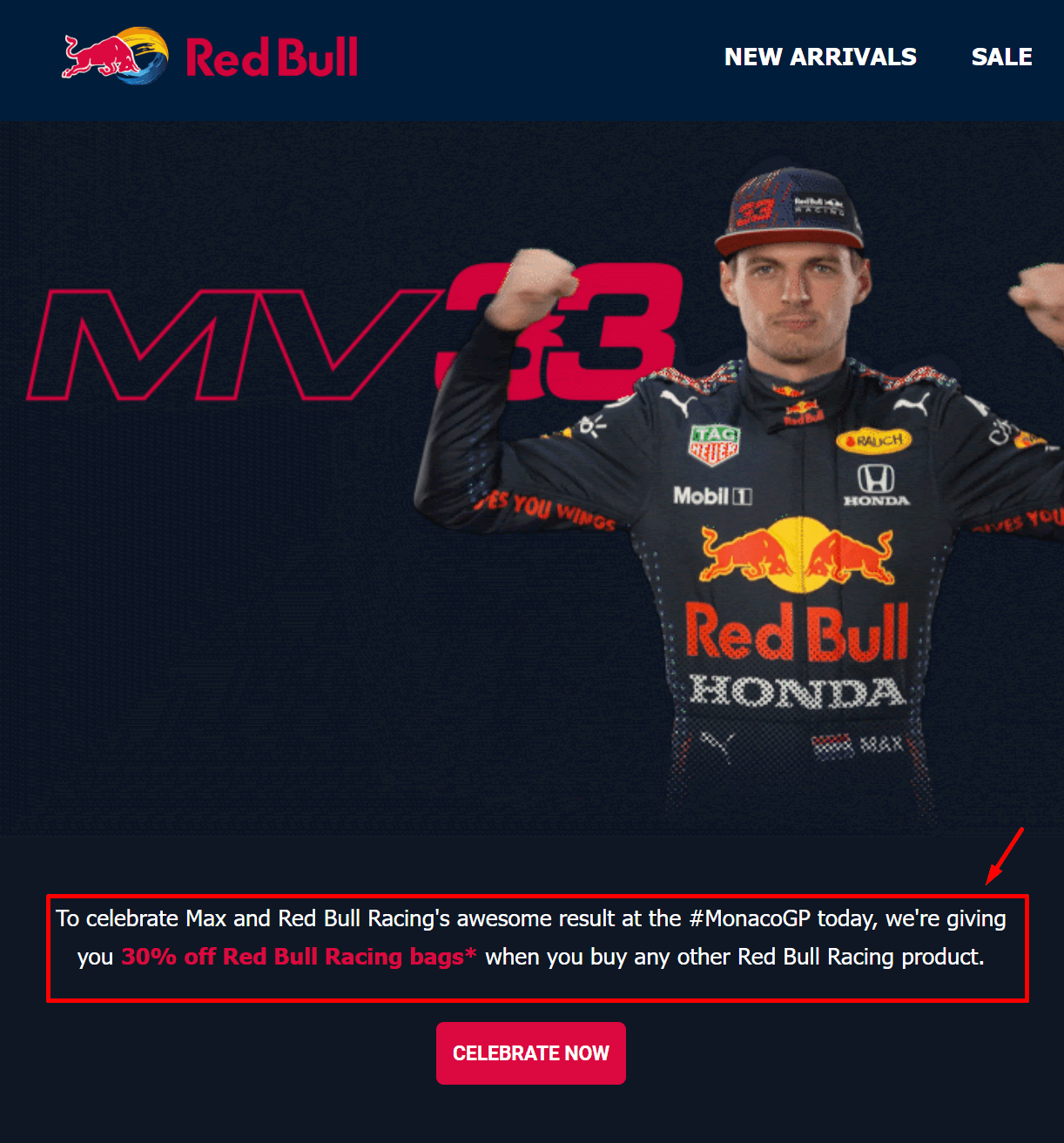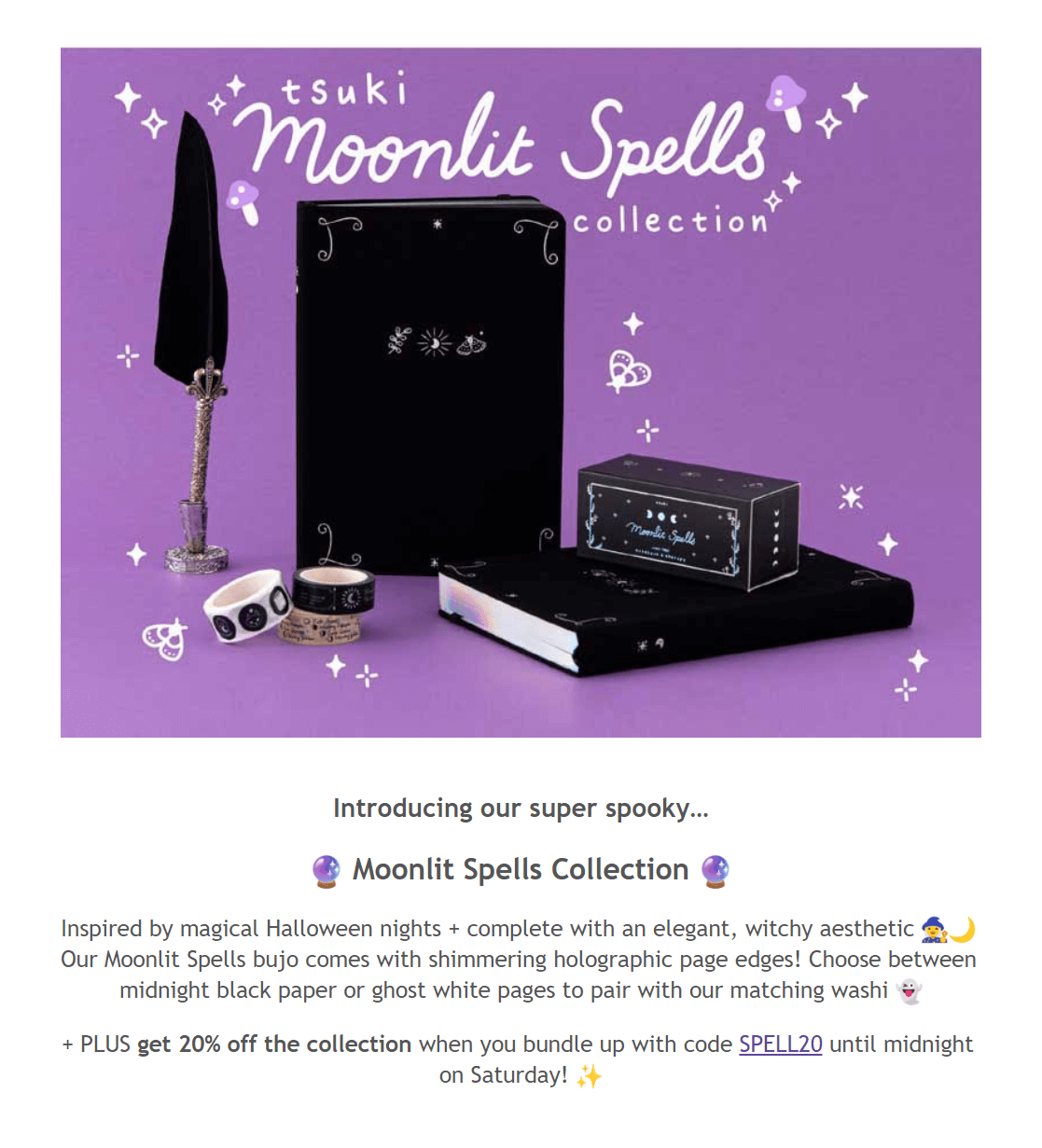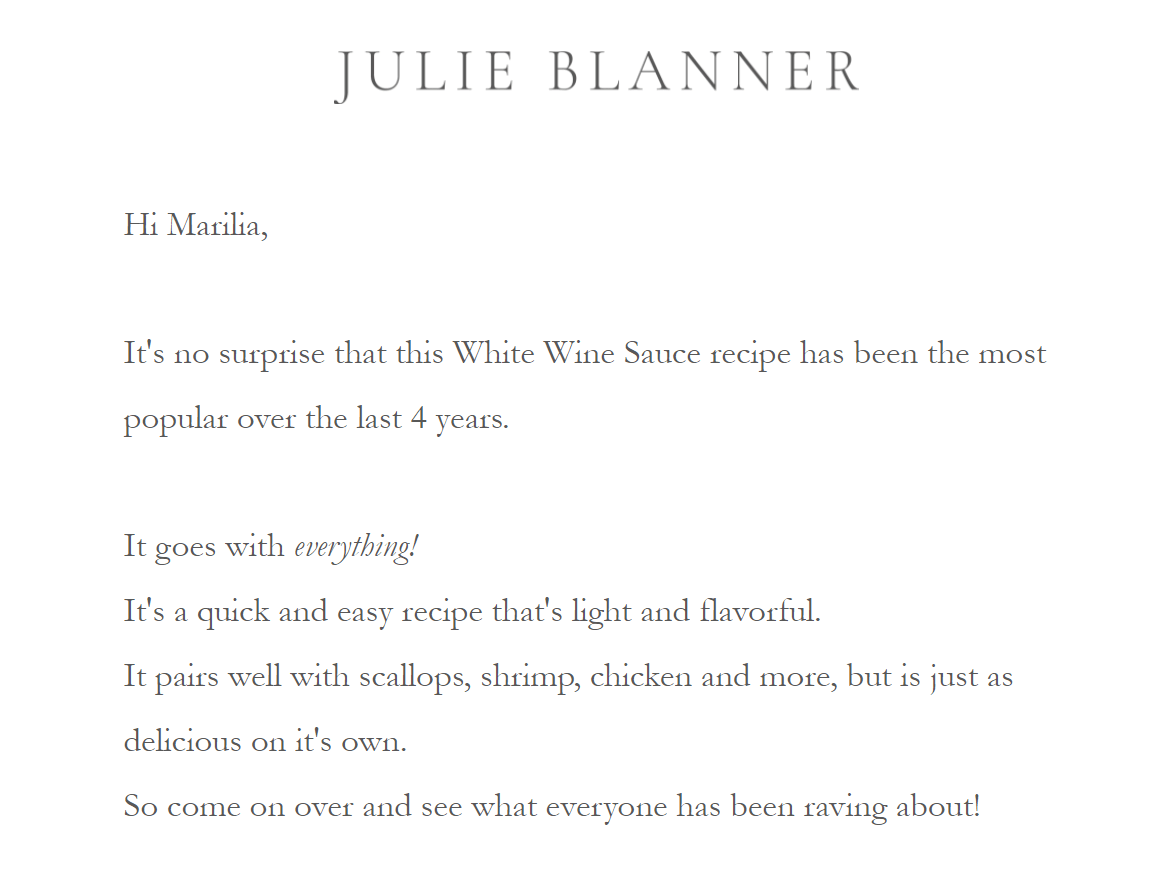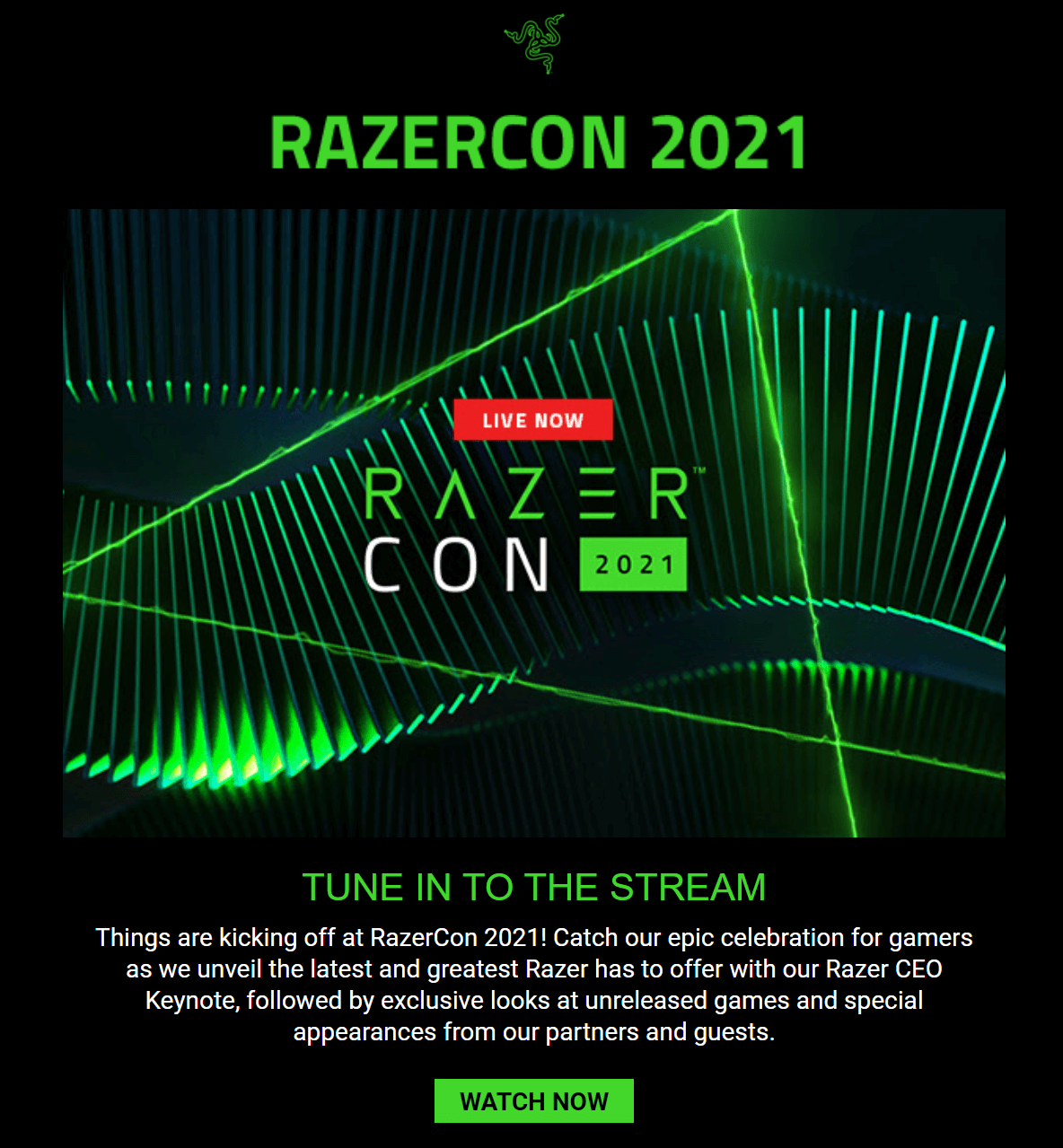
2022 年竞选活动的最佳电子邮件字体 [+Tips]
已发表: 2021-11-15编写您的电子邮件副本是创建时事通讯最重要的部分之一,但您知道为他们选择最好的电子邮件字体可以为其提供动力吗?
如您所知,这些文本的图形表示具有不同的磅值、样式、重量或设计,这为我们提供了过多的字体。 他们每个人都有自己的魅力。
尽管如此,由于有这么多不同的字体可供选择,因此出现了“哪种字体最适合您的电子邮件”的问题。 为了帮助您,今天我们将看到一些很棒的字体和示例,以简化流程!
以下是最适合您的 11 种电子邮件字体选择:
- 英语字体格式一种
- 宋体
- 黑尔维提卡
- 维达纳
- 乔治亚州
- 快递新
- 塔霍马
- 投石机 MS
- 加拉蒙德
- 打开 Sans
- 机器人
电子邮件的顶级字体系列
我们需要做的第一件事是识别各种类型的字体。 基于它们的独特特征,我们可以将这些图形表示分成不同的“家族”。
衬线字体
衬线是在字母末尾使用的线条或笔划。 有这条线的字体称为衬线字体。 “serified”字体的最大优点是它们更加优雅和易读,因为附在字母上的小笔画可以引导读者的视线。 出于这个原因,衬线字体通常用于大块文本!
流行的例子包括 Times New Roman、Palatino、Garamond 和 Georgia。
无衬线字体
这个字体系列的特点是缺少衬线(无衬线实际上意味着没有线条或笔划)。 最常见的无衬线字体是 Arial,Gmail 的默认字体。 无衬线字体非常适合屏幕,因为它们简单且具有现代和简约的结构。
其他常用的无衬线字体包括 Verdana、Geneva、Comic Sans 和 Calibri。
草书字体
这些字体模仿人类的笔迹以达到更自然的效果。 草书字体通常看起来很花哨,如上所述,它们是邀请函和文凭的理想选择,使它们看起来美观。
Lucida Handwriting 和 Edwardian Script 是草书字体的示例。
等宽字体
等宽字体具有相同宽度(固定间距)的字母。 这种字体被打字机和早期计算机使用。 由于等宽字体比非等宽字体更难阅读并且占用更多空间,因此我们将它们用于排版代码。
Courier New 是最流行的等宽字体之一。
幻想字体
Fantasy是另一个字体系列,其中包括看起来更“神奇”的字体。 这些字体非常具有装饰性,因此非常适合书籍、游戏、演示文稿等,因为它们会将任何文本块变成有趣的体验。
著名的幻想字体包括 Papyrus、Herculanum 和 Harrington。
系统界面字体
最后但并非最不重要的一点是,我们拥有系统 UI 字体,这是 Web 排版的新增功能。 这些字体旨在简化网页设计,因为它们不需要网络字体交付服务。 系统 UI 字体允许网页设计师创建感觉现代且用户友好的网站,从而减少加载时间。
流行的系统 UI 字体包括 Roboto、Google 的默认字体、Apple 使用的 San Francisco 和 Mozilla 的 Fira Sans。 当然,我们不要忘记为 Microsoft 设备和操作系统创建的Trebuchet MS 。
既然您了解了字体系列,那么您如何为下一个电子邮件设计选择合适的字体系列? 好吧,在选择字体之前,有必要了解一下所谓的网络字体和网络安全字体。 让我们来看看!
网络字体与。 网络安全字体
首先,网络字体不应该与网络安全字体混淆。 原因很简单。
网络安全字体是在每个操作系统上都可以找到的字体,这意味着它们具有浏览器适应性,即使您从设备上卸载它们,它们也可以在每台设备上显示。 另一方面,Web 字体可能无法在每台计算机或操作系统上找到。 因此,如果您使用它们而您的收件人没有安装它们,您的文本可能无法为他们正确呈现。
这种差异清楚地表明,如果您想选择最好的电子邮件字体,您需要它们是网络安全的,或者更准确地说,是电子邮件安全的:
如您所见,营销人员现在可以使用更多种类的网络安全 CSS 和 HTML 字体,从而为他们的业务创建独特的品牌标识。
然而,当你真的需要使用像 Poppins 或 Inter 这样的网络字体时会发生什么? 好吧,在这种情况下,您需要了解支持它们的电子邮件客户端。
哪些电子邮件客户端支持 Web 字体?
为您的时事通讯选择正确的字体对于提供独特的用户体验至关重要。 例如,Cox & Cox 在他们的电子邮件营销活动中使用无衬线 Gill Sans 字体:
使用网络字体可能听起来并不理想,但如果你先考虑几件事,你绝对可以使用它们。 最重要的是找出哪些电子邮件客户端与他们配合得很好:
- 苹果邮件和 iOS 邮件
- Outlook 2000 和 Outlook.com 应用程序
- 三星邮件
- 安卓邮件客户端
此外,根据最近的一项调查,五分之三的顶级电子邮件客户端支持网络字体,因此使用它们可能不是一个坏主意。 您需要考虑的下一件事是从哪里获取它们以及如何将它们嵌入到您的时事通讯中。
选择后备字体
使用网络字体进行电子邮件营销时,您需要记住的最重要的事情是实现备用字体。
简而言之,当您的第一个字体无法显示时,会使用备用字体。 因此,如果您的收件人的电子邮件提供商无法呈现您的网络字体,它将使用备用字体。 为了使它们起作用,您的后备字体应该在粗细、宽度和 x 高度方面与您使用的原始字体相似。
如果我们回到 Cox & Cox 的电子邮件活动,我们可以通过单击“检查”选项检查 Gill Sans 网络字体的后备字体。 如您所见,Arial 和 Helvetica 是在电子邮件客户端无法显示 Gill Sans 时使用的两种字体:
虽然遵循上述内容将帮助您提供正确呈现的时事通讯,但改善订阅者阅读体验的最佳方法是根据数据进行字体选择!
找出您的大多数订阅者用来打开您的广告系列的内容将允许您选择最佳的电子邮件字体,并为他们提供看起来非常完美的优化 HTML 电子邮件。
电子邮件活动的 11 种最佳字体
现在让我们为您的消息检查顶级网络安全字体和一些网络字体!
1. Times New Roman – 电子邮件安全字体
Times New Roman 是目前最流行的衬线字体之一。 它被归类为混合的旧式过渡字体,主要用于书籍等印刷材料。 Times New Roman非常适合标题和正文,因为衬线字体以提高可读性而闻名。
示例:凹凸
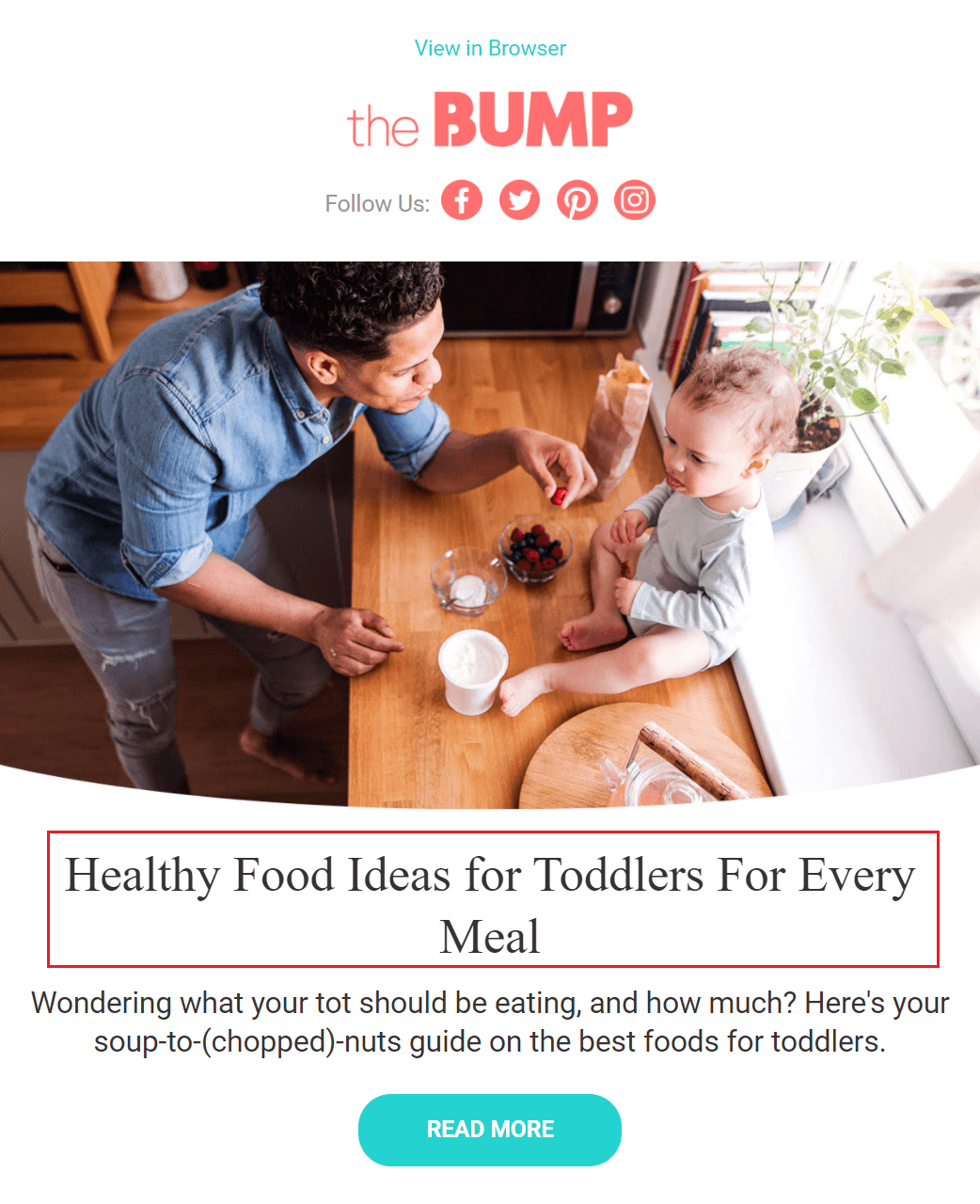
Bump 利用这种易于阅读的字体使其标题流行。 除了 Times New Roman,该品牌还使用 Roboto 网络字体作为正文。
虽然这两种字体搭配得很好,但重要的是选择让您的新闻稿模板看起来专业且平衡的组合。 糟糕的组合可能会破坏读者的体验并导致沮丧,因此请先测试不同的字体,然后再做出最终决定!
2. Arial - 电子邮件安全字体
Arial(或 Arial MT)是另一个不错的选择,因为它是大多数网站和浏览器的默认字体堆栈无衬线字体。 它适用于标题和其他小型电子邮件元素,因为它是在考虑计算机屏幕的情况下开发的。 虽然由于其可访问性而成为一种流行的选择,但它对于大块文本可能并不完美,因为它不像 Helvetica 等其他字体那样具有可读性。
此外,Gmail 使用 Arial,因此最好记住这一点,以防您的大部分电子邮件都是通过它打开的。
示例:斐乐
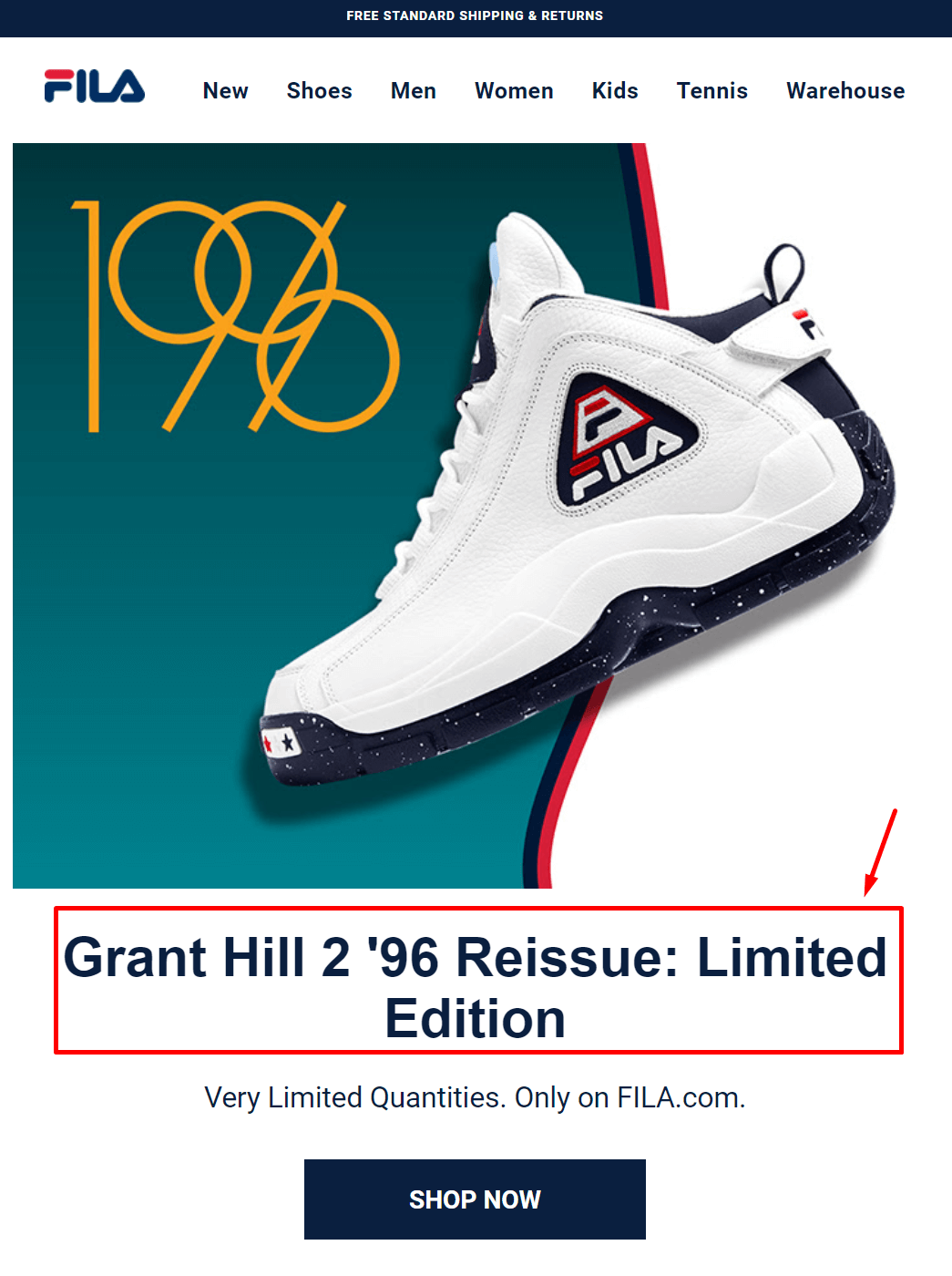
Fila 是一个遵循特定电子邮件通讯活动模式的品牌。 它通常有很多产品图片,并附有粗体标题和简短描述。 为了使这些描述流行起来,该品牌使用 Arial 字体,如您在上面的示例中所见。 此外,它通常将 Arial 与另一种无衬线字体 Roboto 配对,以创造令人愉悦的效果。
3. Helvetica – 网络安全字体
Helvetica(或 Neue Haas Grotesk)是另一种新怪诞的无衬线字体。 这种字体与它的表亲 Arial 具有相同的优点,它是您的时事通讯标题的不错选择,因为它具有大胆和现代的外观,可以让您的文本脱颖而出。 该字体是商业电子邮件的绝佳选择,因为它将赋予它更专业的氛围。
Helvetica 也是 Apple Mail 使用的默认字体,所以如果您的读者是 Mac 用户,请记住这一点!
示例:从实验室到美容
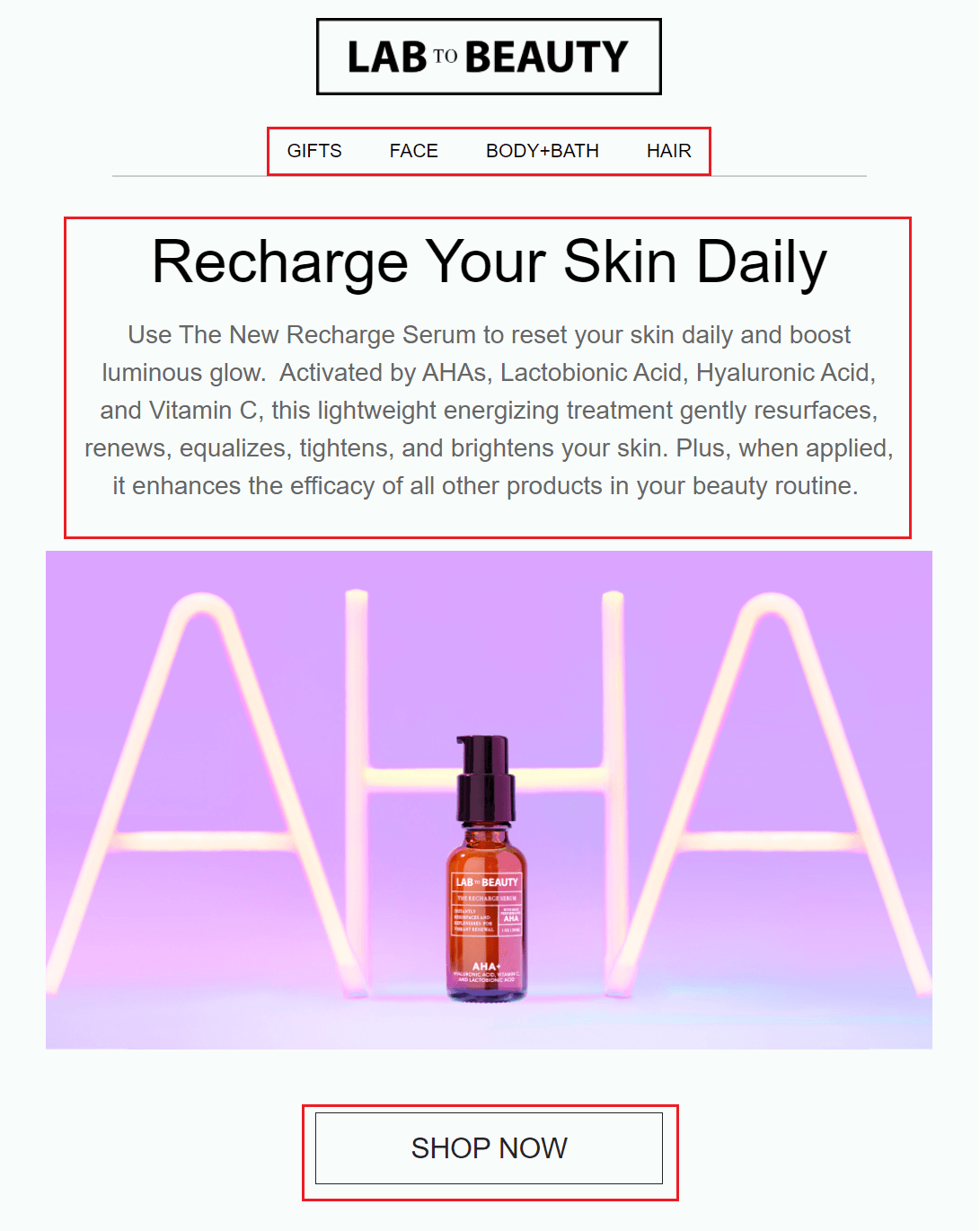
Lab to Beauty 将 Helvetica 和 Helvetica Neue 用于其导航栏、标题、正文和号召性用语。 除了简洁的电子邮件通讯外,该品牌还使用这种流行的字体来创建平衡的电子邮件,放大其现代精神。
4. Verdana - 网络安全字体
Verdana 是另一种无衬线字体,其独特之处在于它在字母之间增加了空间以增加易读性。 因此,这种字体是您广告系列的最佳电子邮件字体之一,因为它可以改善用户体验并且比 Helvetica 和 Arial 表现更好。
示例:哈利的
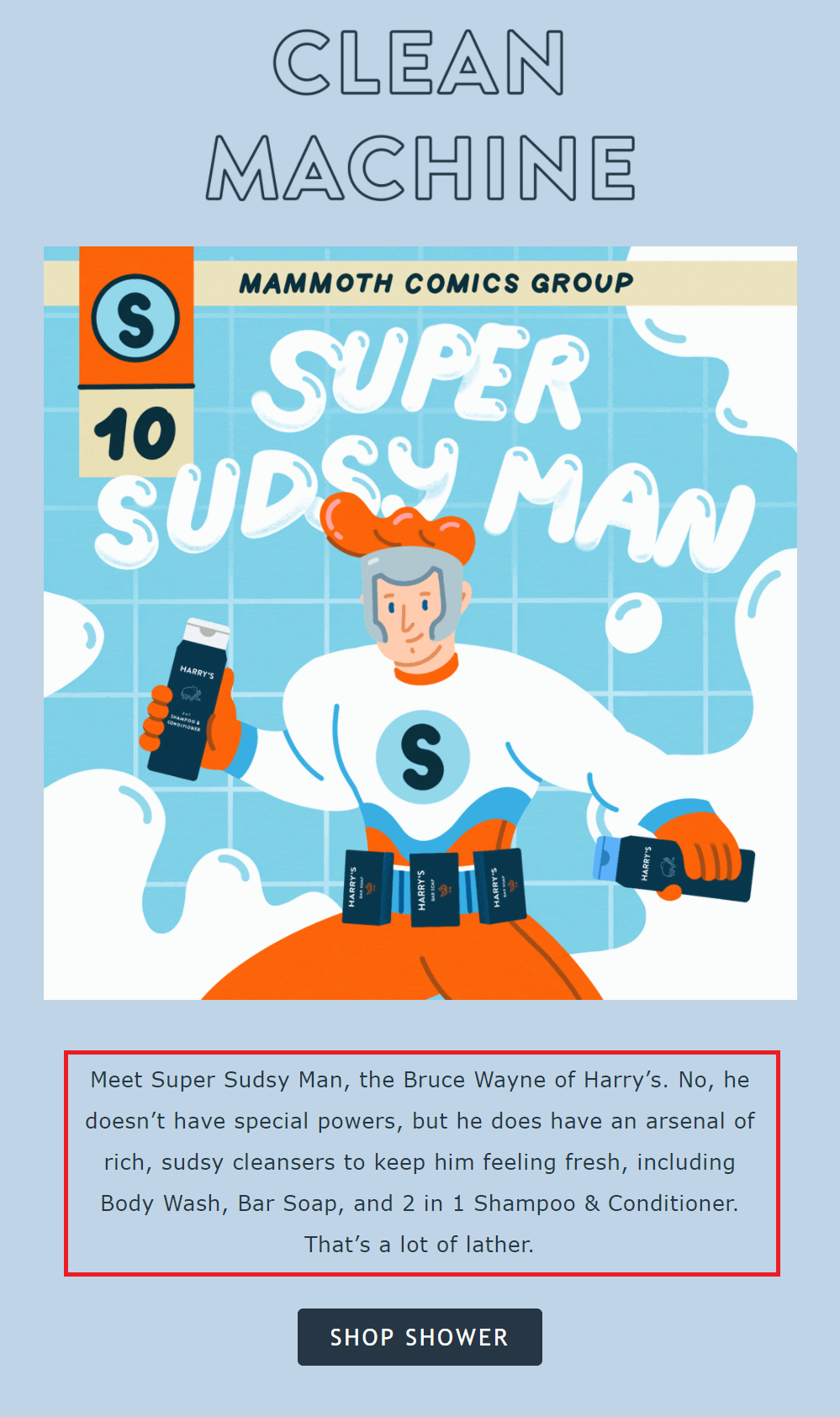
Harry's 使用 Verdana 使其正文更易于阅读。 此外,该品牌选择将其与 Gill Sans(见 CTA)配对以改善阅读体验。
最重要的是,字体与品牌的视觉效果很好地融合在一起,给广告系列带来了一种非常现代和俏皮的感觉。
5. Georgia – 网络安全字体
Georgia 是一种衬线字体,可为您的标题和电子邮件副本增添优雅。 由于它与 Times New Roman 类似,您将获得流行的 serif 字体的所有好处,并受益于Georgia 更圆、更粗的字体样式。 该字体也是一种非常易于访问且对网络安全的字体,因此您可以使用它为您的观众提供现代体验。
示例:威尼斯度假村
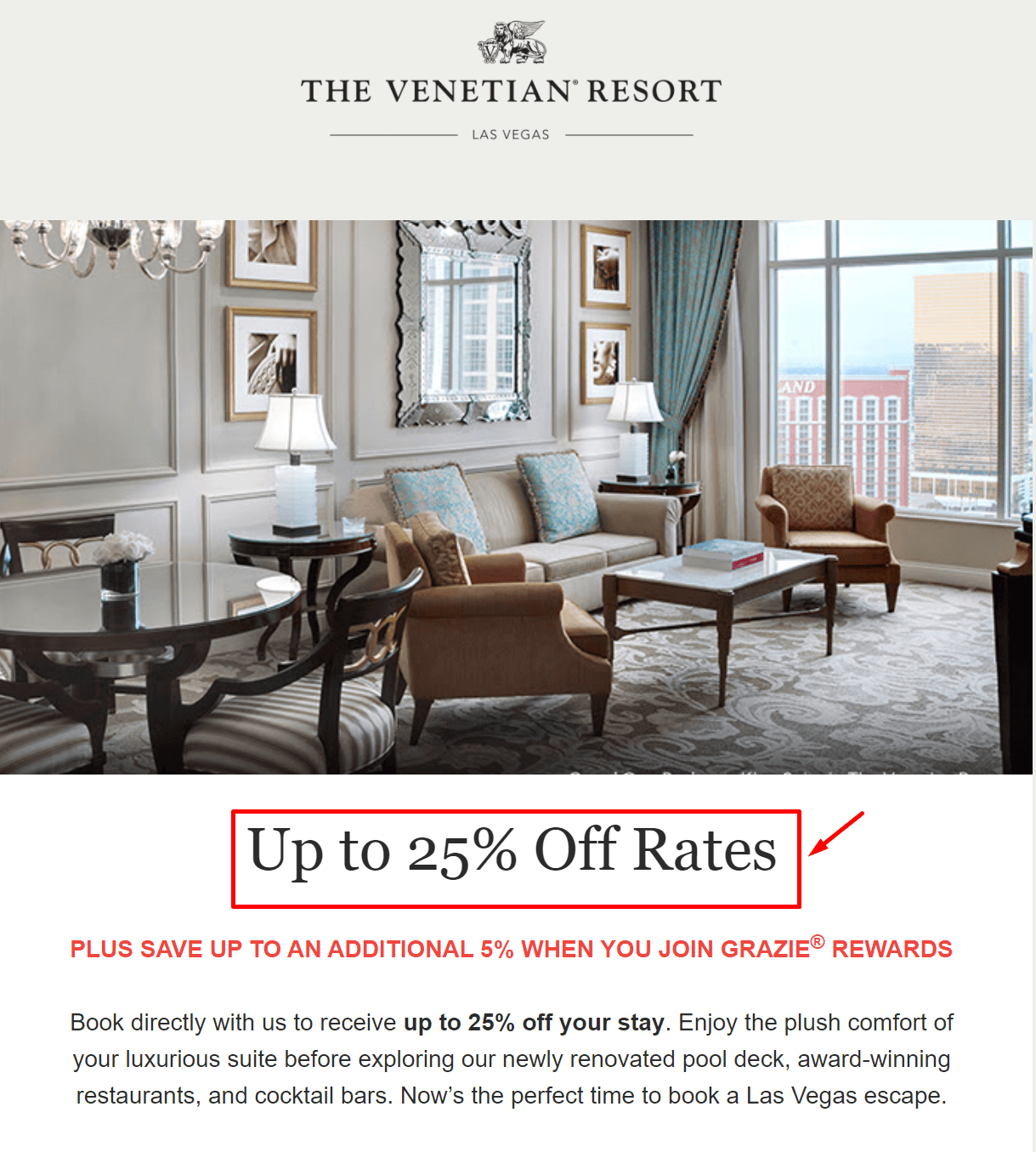
威尼斯人度假村利用衬线字体使其标题更加时尚和独特。 如上所述,Georgia 是 Times New Roman 的绝佳替代品,它会增加文本的易读性,从而带来更好的阅读体验和转换!
6. Courier New - 电子邮件安全字体
如果您想让您的读者从过去中汲取灵感,您可以利用 Courier 和 Courier New。 这种等宽衬线字体是为 IBM 的打字机开发的,所以如果你使用它,你会立即给你的正文文本一种古老的氛围。 Courier 非常适合创建具有更“老式”或“质朴”感觉的品牌电子邮件通讯模板。 让我们看一下示例!
示例:崇拜的复古
Adored Vintage 使用与其产品和品牌标识相一致的字体来加强他们的品牌游戏。 虽然 Courier 可能不是您的首选,但将其用于像这样的特定活动将帮助您创造一种体验,而不是简单的促销信息。
#3。 电子邮件的理想字体间距是多少?
字母间距取决于您选择的字体,因为字体系列具有不同的字符宽度。 尽量不要选择没有大的正或负间距值的字体,以保持良好的易读性。
#4。 我可以在我的字体中使用样式元素吗?
使用粗体、斜体和字体颜色等样式元素取决于您的电子邮件通讯设计以及是否需要强调特定的文本块。 对于标题,您可以使用所选字体集的现有粗体版本。
#5。 什么是最好的电子邮件字体?
基于其易读性和电子邮件客户端兼容性,电子邮件通讯的最佳字体是网络安全(电子邮件安全)字体,包括 Arial、Verdana、Georgia、Helvetica 和 Times New Roman。 不过,您可以使用 Open Sans 和 Roboto 等网络字体,但不要忘记设置备用字体。
#6。 桌面电子邮件客户端的默认字体是什么?
每个电子邮件客户端都有不同的默认字体来显示您的文本。 Gmail 使用 Arial,Apple Mail 使用 Helvetica,Microsoft Outlook 使用 Calibri。